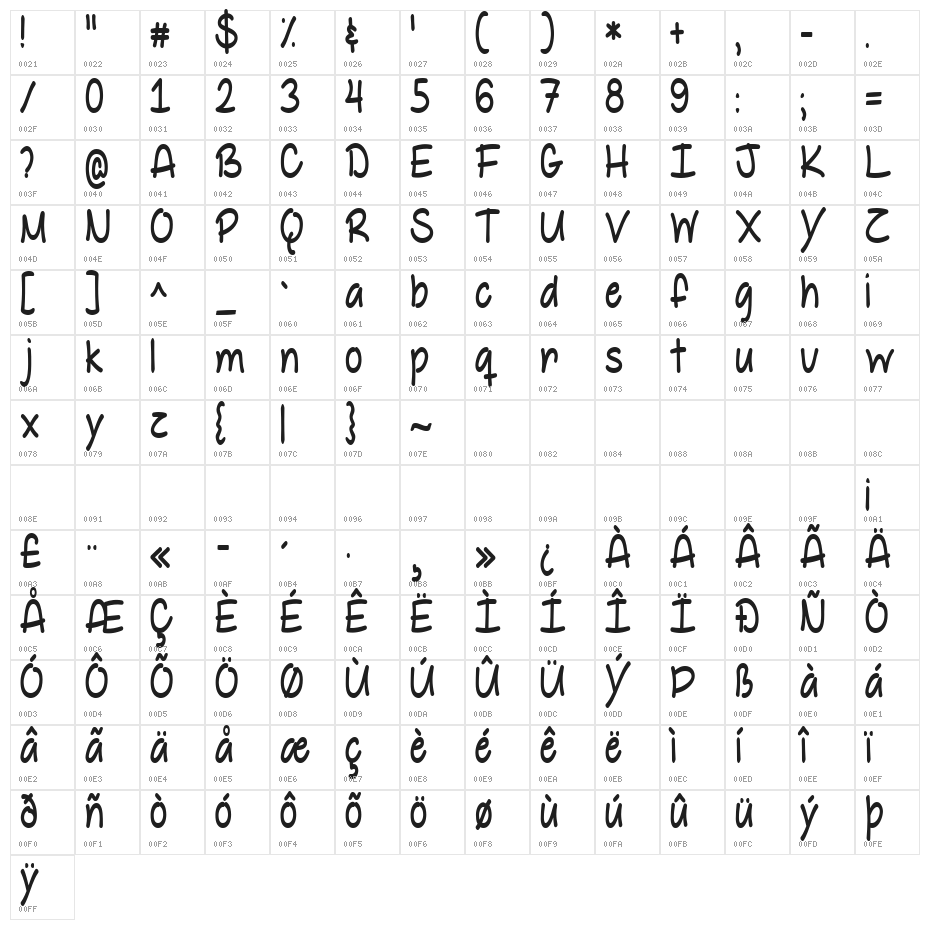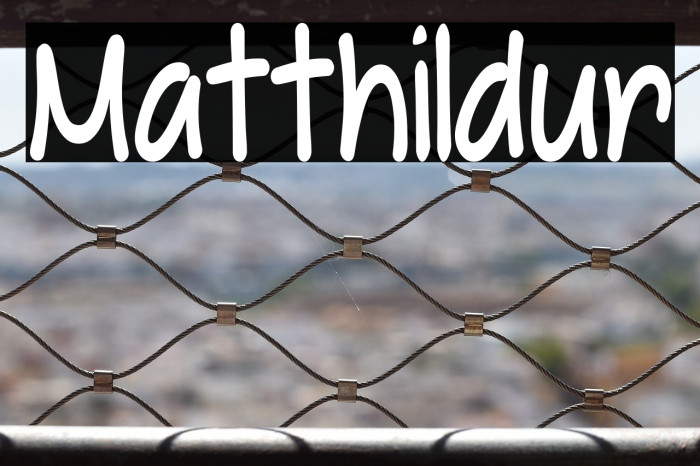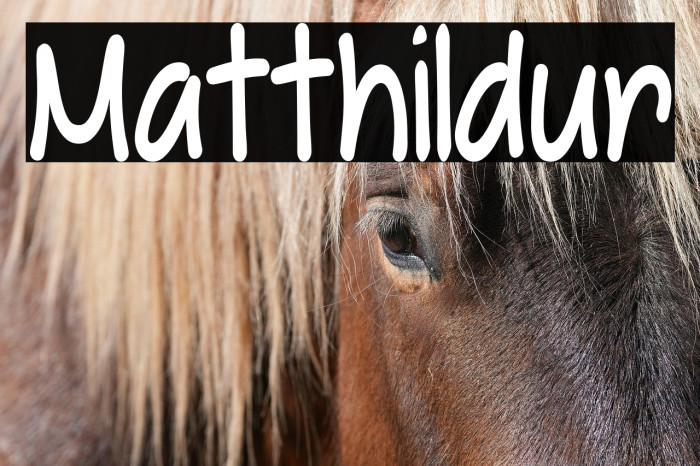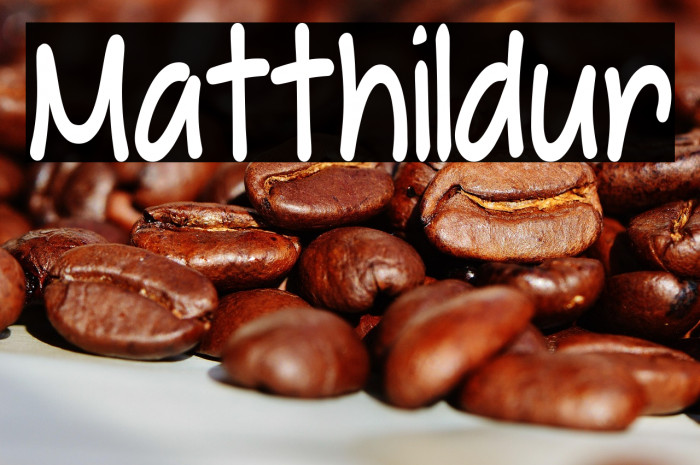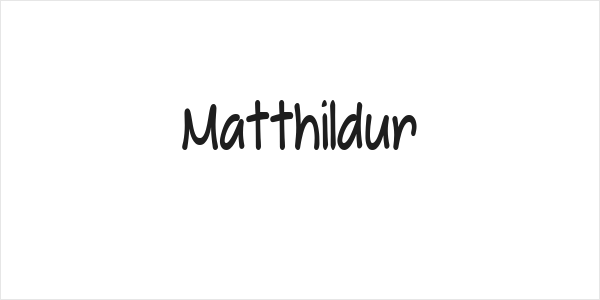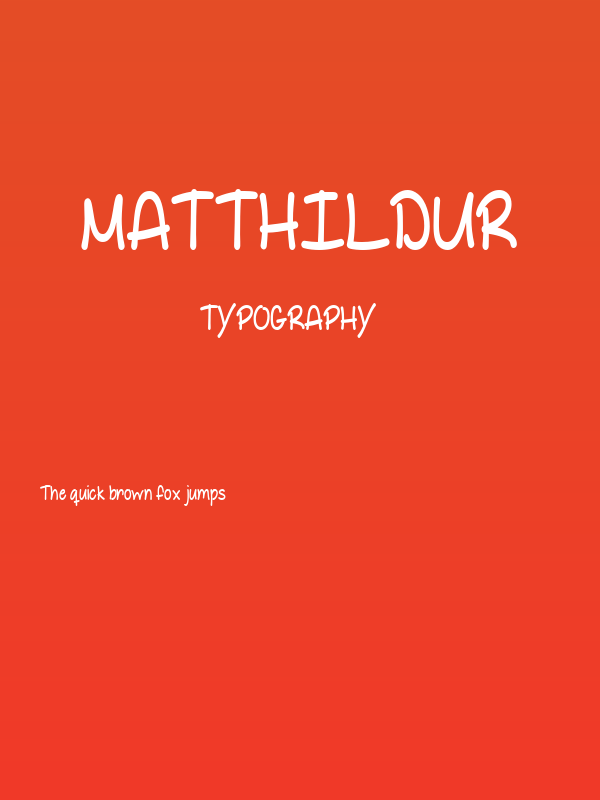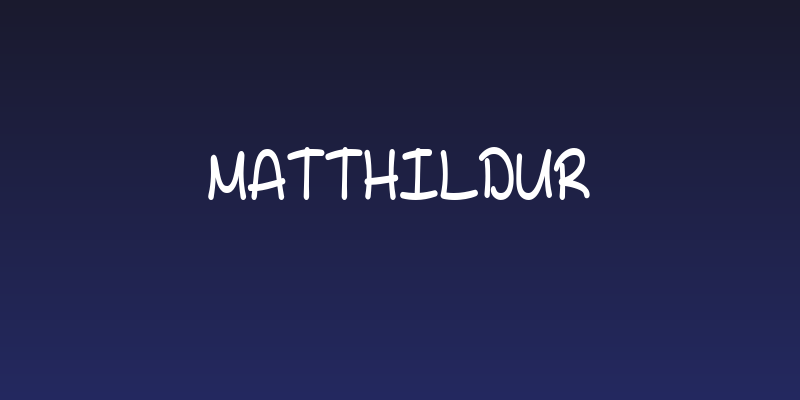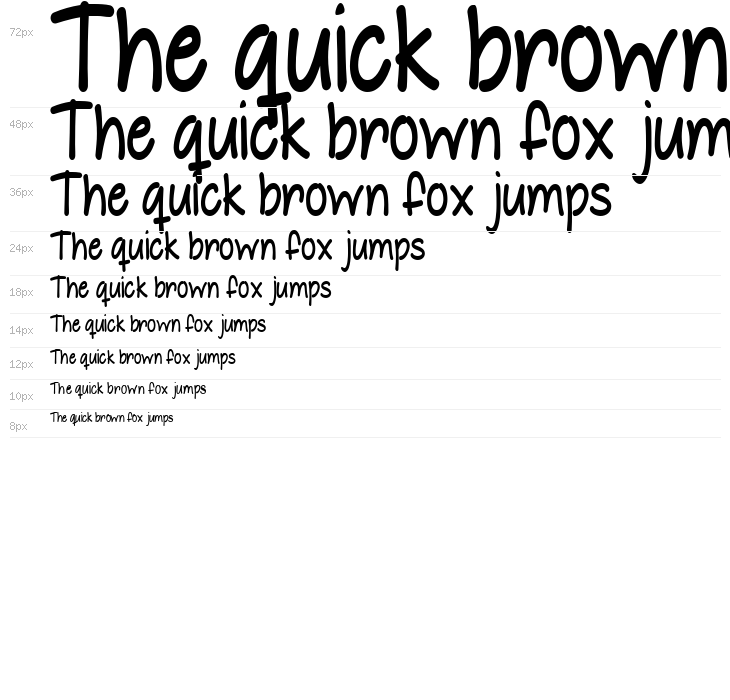
Matthildur Font
MATTHILDUR MAIUSCOLE
MATTHILDUR MINUSCOLO
MATTHILDUR ALTRI CARATTERI
| Stile generale | Casual |
| Caso d'uso | Headlines, Logos, Informal Text |
| Progetti proposti | Ideal for children's books, greeting cards, informal branding, and playful designs. |